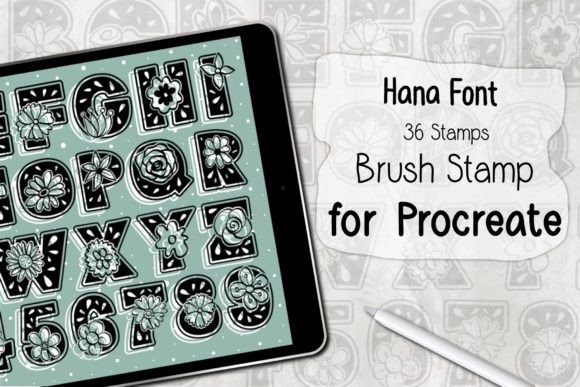
Hana Font Procreate Brush Stamp
Znalezienie odpowiednich elementów projektu może być wyzwaniem, ale Hana Font Procreate Brush Stamp oferuje wyjątkową kolekcję, która natychmiast ulepszy Twoją pracę.